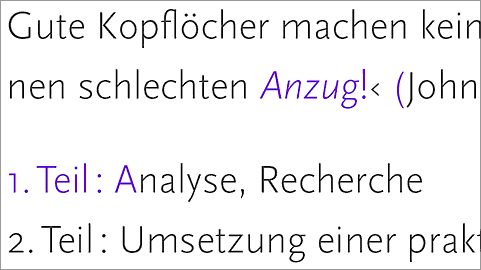
Auch auf die Gefahr hin dass dieser Thread In TypoTalk besser aufgehoben wäre, stelle ich nun hier meine vier kleinen Fragen:
1. "Anzug!": Setze ich Interpunktionszeichen nach einem einzelnen ausgezeichneten Wort in der normalen Fließtextschrift, oder, weil das Interpunktionszeichen am vorgestellten Wort "dranhängt" und auch schöner aussehen würde, im auszeichnenden Schnitt?
2. "1. Teil": Mit normalem Leerzeichen zwischen "1." und "Teil" sieht der Abstand zu groß aus; ich verwende deswegen ein Achtelgeviert. Wie macht ihr das?
3. Leerraum vor Doppelpunkt: entfällt, ist ja nur im französischen so.
4. Die runden Klammern sitzen bei der hier verwendeten Scala für meinen Geschmack ziiiemlich tief. Kann mir das jemand erklären?
(Bei der FF Nexus Sans oder der John Sans oder der Gill Sans ist das auch so.)
4. Die runden Klammern sitzen bei der hier verwendeten Scala für meinen Geschmack ziiiemlich tief. Kann mir das jemand erklären?
Die sitzen doch perfekt auf x-Höhe, oder? Ich würde mal vermuten, daß das daher kommt. Beim en-dash ist das ja bei vielen Schriften auch so. Der paßt als Gedankenstrich sehr gut, sitzt aber zu tief als »von-bis-Strich« wenn man keine Mediävalziffern verwendet. Das mathematische Minus-Symbol ist hingegen wieder auf die Zahlen zugeschnitten und damit oftmals höher.
Das folgende Satzzeichen wird, soweit ich mich erinnere mit ausgezeichnet. Bei der Geschichte mit dem 1. Teil etc. würde ich einfach meine Augen gebrauchen. Der Abstand ist wohl sehr groß vor dem "T", so dass es fast aussieht als ob da Erstens steht. Mach es einfach kleiner bis es gut ausschaut, ob das ein Achtel oder was auch immer ist.
Die sitzen doch perfekt auf x-Höhe, oder? Ich würde mal vermuten, daß das daher kommt.
Tatsache, das scheint der Grund zu sein. Befriedigt mich noch lange nicht, ich bin immer vesucht die Klammern einen Punkt hochzusetzen... Guckt euch doch mal die Gill an, wie sieht das denn aus! (Ja, ich rege mich gerne künstlich auf.)
Das folgende Satzzeichen wird, soweit ich mich erinnere mit ausgezeichnet.
Das Guillemet etwa auch? (In dem Beispiel hier.)
Bei der Geschichte mit dem 1. Teil etc. würde ich einfach meine Augen gebrauchen.
Das ist natürlich prinzipiell richtig, lässt sich jedoch im Fließtext (zeitlich) nicht umsetzen, zumindest in meinem Fall.
1. Ich würde das Ausrufezeichen nicht auszeichnen, außer es wäre deutlich mehr ausgezeichnet (zum Beispiel der ganze Satzteil)
2. Normalerweise nehme ich da schon ein ganzes Leerzeichen, aber in deinem Fall ergibt sich zwischen Punkt und „T“ eine große Lücke, deshalb ist ein Achtelgeviert natürlich problemlos nachvollziehbar. Wenn die Auflistung noch länger ist, könnte sich evtl. ein Listenabsatzformat lohnen, bei dem du den Punkt nach der Zahl an einem Tabulator ausrichtest und die Zahl davor rechtsbündig machst.
4. Ich hab die Scala nicht, aber vielleicht hat sie ja kontextabhängige Glyphen. Extra hochsitzende (kurze) Klammern für Kapitälchen sind bei gut ausgebauten OT-Schriften durchaus nicht unüblich.
Ich glaub das steht im Duden. Nur das nachfolgende Zeichen, nicht das Guillemet.
Ich muss mich da korrigieren. In meinem Duden steht:
"Wird in einem Satz ein einzelnes Wort (...) ausgezeichnet (fett, halbfett, ...), so gehört das Satzzeichen (Punkt, Komma, ...) mit zum Grundtext und wird nicht ausgezeichnet."
Na, da hab ich es bisher immer falsch gemacht. So ein Mist.
Und noch ein Zusatz: Wenn (typografisch :D )ausgezeichnete Wörter am Ende des Satzes stehen, wird der Punkt aus optischen Gründen mit ausgezeichnet.
Da steht nur "Schlusspunkt". Von Ausrufezeichen steht da nix, also nö!
In meinem Duden steht:
"Wird in einem Satz ein einzelnes Wort (...) ausgezeichnet (fett, halbfett, ...), so gehört das Satzzeichen (Punkt, Komma, ...) mit zum Grundtext und wird nicht ausgezeichnet."
Vor vielen Jahren (das wird wohl irgendwann Anfang der 90-er gewesen sein) hat mir die Duden-Redaktion auf eine entsprechende Anfrage geantwortet, dass in so einem Fall das Zeichen wie das Wort, an dem es dranhängt, behandelt wird. Offensichtlich hat sich das inzwischen geändert.
Man könnte außerdem noch "1. Teil" / "2. Teil" bündig ausrichten, z.B. durch Verwendung von Tabellenziffern.
ich neige ja – und hier geht es offensichtlich eh mehr um meinungen als um feste regeln – der meinung zu, dass das satzzeichen zum grundtext gehört und nicht ausgezeichnet wird. der inhalt soll ja hervorgehoben werden; satzzeichen strukturieren den inhalt.
Wenn (typografisch) ausgezeichnete Wörter am Ende des Satzes stehen, wird der Punkt aus optischen Gründen mit ausgezeichnet.
hier glaube ich, dass in diesem satz das inhaltliche schwergewicht auf »am ende des satzes« liegt und nicht auf dem wort »punkt«, so dass es, sinngemäß interpretiert heißen müsste: »am ende des satzes ... wird das der auszeichnung folgende satzzeichen ... mit ausgezeichnet.«
In meinem Duden steht:
Immer wieder staun ich, mit welcher Ergebenheit dem Duden gehuldigt wird unter gleichzeitiger Ablehnung der Rechtschreibreform (oder auch der Groß-/Kleinschreibung ...) :neenee:
Um Dich etwas zu versöhnen: Ich habe mich damals trotzdem nicht streng daran gehalten: Für die hochgestellten Fußnotenziffern im Text erschien mir dieses Vorgehen falsch.